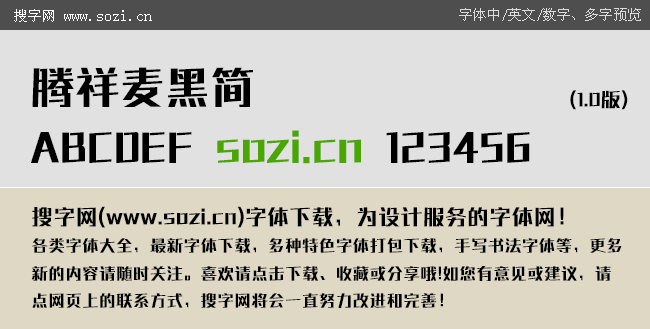
騰祥麥黑簡(jiǎn)
搜字網(wǎng)提供一款騰祥麥黑簡(jiǎn)中文藝術(shù)字體下載。騰祥麥黑簡(jiǎn)字體是一款非常具有設(shè)計(jì)感的藝術(shù)美容院體,簡(jiǎn)潔大方,端正大氣,所以該字體可適用于廣告設(shè)計(jì)、平面設(shè)計(jì)、包裝設(shè)計(jì)等方面。